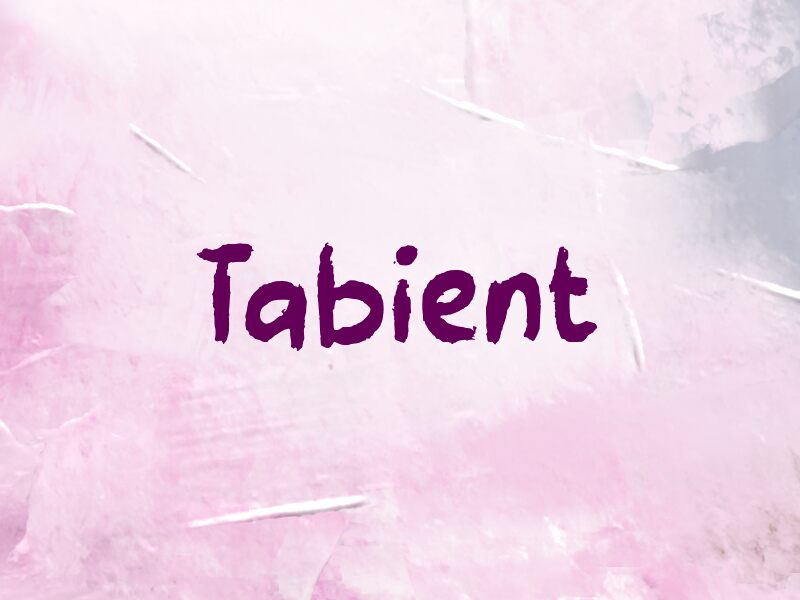
Tabient
Tabient od Wep je bezplatné písmo typu štetec (brush), definované širokými ťahmi atramentu, ktoré pôsobia dojmom pritlačeného ťahu a miernej nepravidelnosti namiesto strojovej presnosti. Tento drsný povrch dodáva písmenám rytmus ručnej maľby s mäkkými škvrnami, tupými koncami a tmavou, vlhkou textúrou, vďaka ktorej pôsobí celý dizajn uvoľnene a hmatateľne.
Tabient vynikne na plagátoch, obaloch albumov, menu v kaviarňach, obaloch výrobkov a grafike pre sociálne siete, kde táto maľovaná textúra znamená viac než len obyčajný nápis. Keďže si tvary zachovávajú plnosť a oblosť aj pri svojich rozstrapkaných okrajoch, skvele poslúži v krátkych nadpisoch, logotypoch aj promo akciách, bez toho, aby stratil ten surový charakter fixky a štetca, ktorý mu dodáva jeho jedinečný pôvab.